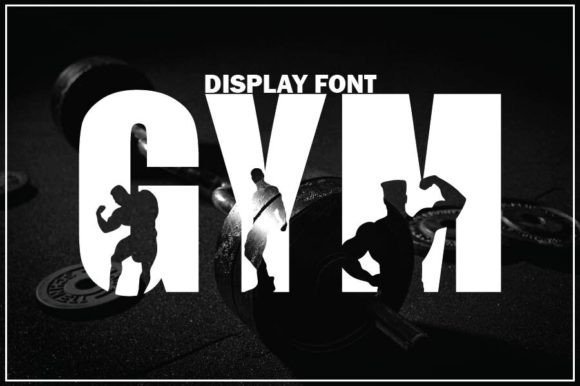
Gym Font
Gym Font – الخط المثالي لعشاق اللياقة والتصميم الرياضي
امنح تصاميمك قوة وحيوية مع Gym Font، الخط العصري المصمم خصيصًا للمشاريع المرتبطة باللياقة البدنية، كمال الأجسام، والرياضة. يتميز بتصميم قوي وحواف حادة تعكس الطاقة والحركة، مما يجعله الخيار الأمثل للشعارات، البوسترات، محتوى وسائل التواصل الاجتماعي، وتصميم الملابس الرياضية.
✅ تصميم عصري وقوي يناسب العلامات التجارية الرياضية
✅ مثالي للشعارات، البانرات، والبوسترات التحفيزية